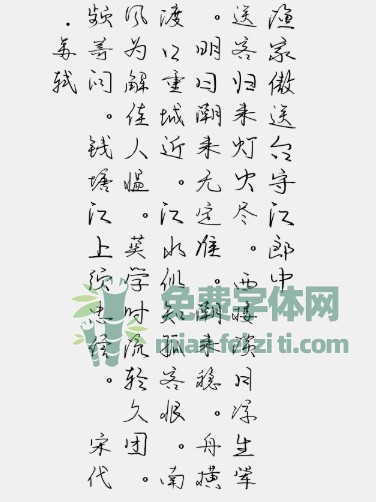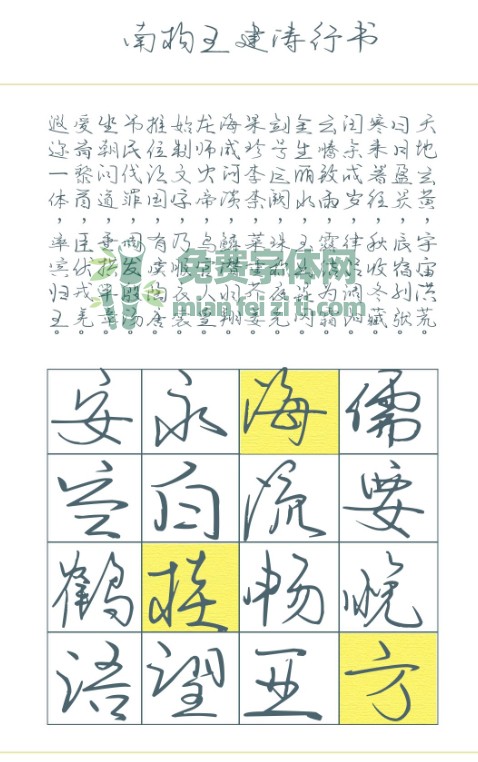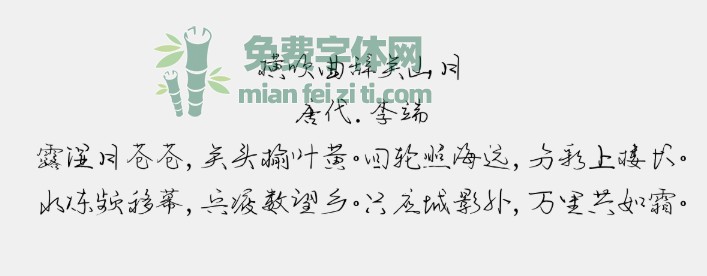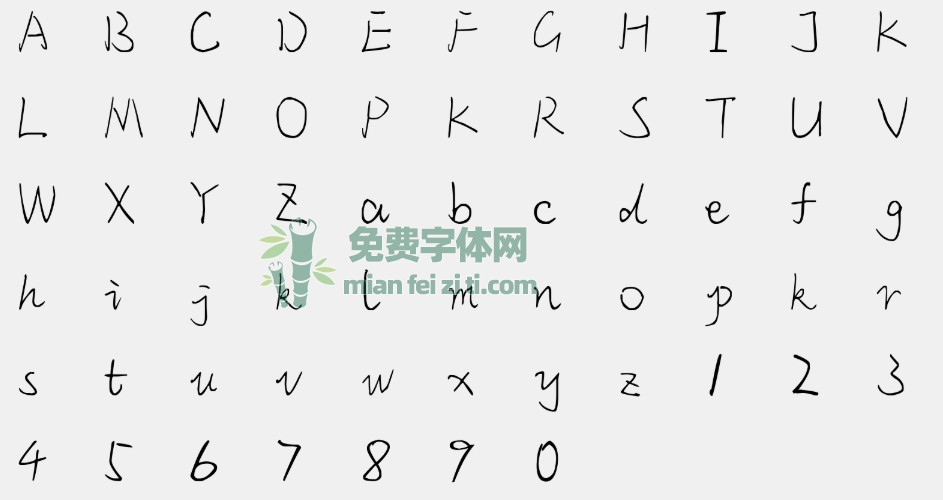
南构王建涛行书预览及介绍
南构王建涛行书
王建涛,毕业于西南大学经济管理学院。因家庭环境影响,自小就对于文字有浓厚的兴趣。初中时承蒙孟莲君老师(山东省章丘市实验中学语文组教师)发掘,开始临摹字帖,彼时写字已“颇有大人的味道”,调皮捣蛋帮助同学代签家长意见也不在话下。大学时期,于西南大学校刊《热地》编辑部任文字编辑三年,闲暇时间,写字的爱好也不曾落下,并于2015年、2016年西南大学书法大赛两次参赛并侥幸获二等奖。喜欢臭美,喜欢在社交平台上分享自己的拙作,因此才得以被字体家公司发现,圆了儿时天真的梦,并开启了更艰深的破冰之旅。
字体特点
这款南构王建涛行书字体是一款趋于自然书写风格的毛笔行书字体,一款有温度的手写体,由字体爱好者王建涛书写创意,自然手写,字形流畅,良好流畅的笔画表现,使这款字体很有视觉冲击力,在对联应用,标题海报使用都非常的不错。